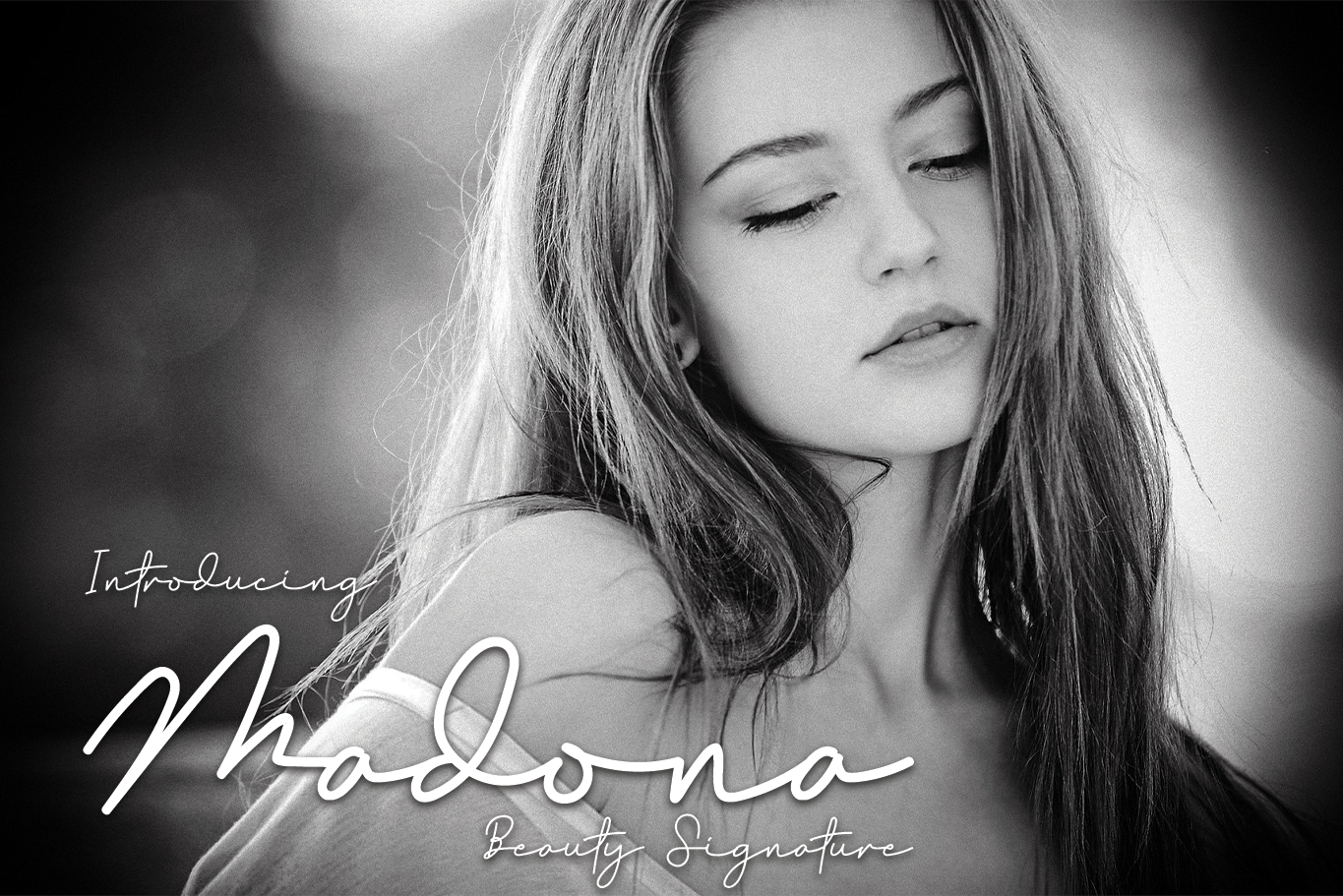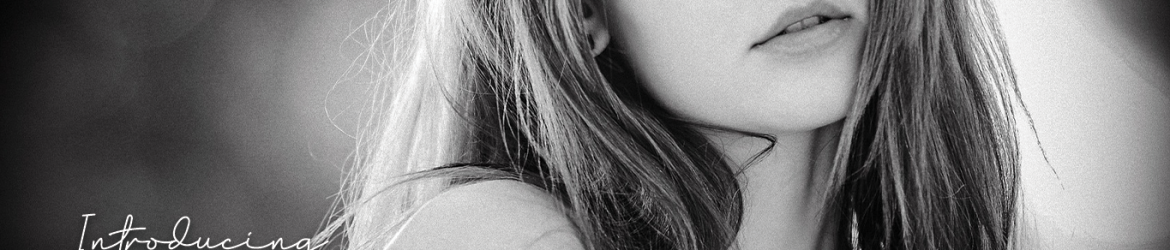
Madona Font – Download Grátis
A Madona Font é uma elegante caligrafia escrita à mão que transmite sofisticação e classe. Este tipo de font foi meticulosamente projetado para aqueles que desejam um aspecto fresco e atraente em seus designs, oferecendo uma abordagem refinada às suas criações. Com sua delicadeza e sutileza na escrita, ela é ideal tanto para gráficos corporativos quanto para designs pessoais. A Madona é perfeita para aqueles que buscam um toque único e sofisticado em seus trabalhos de design, sem comprometer a elegância.